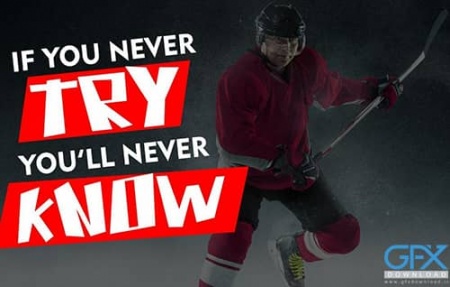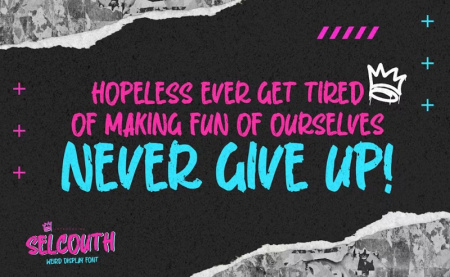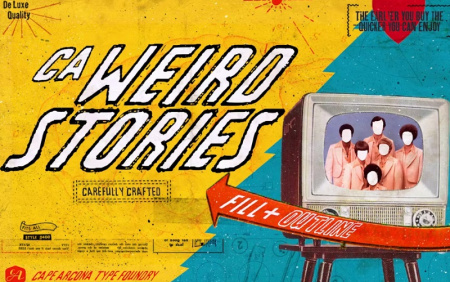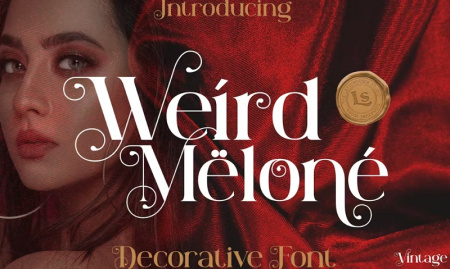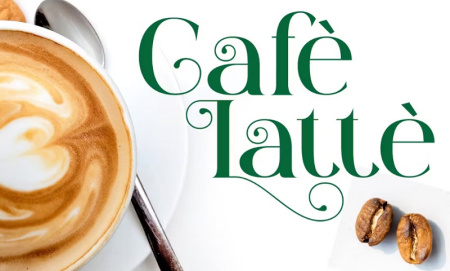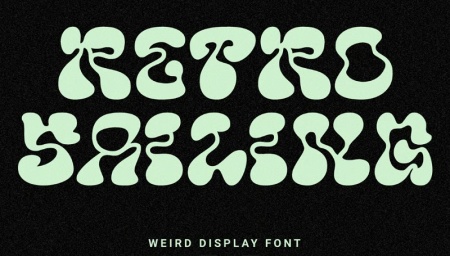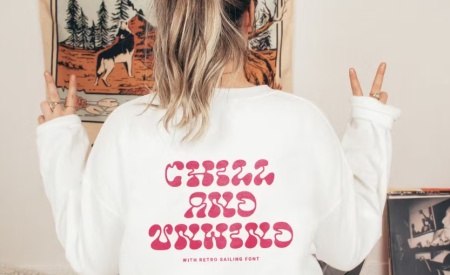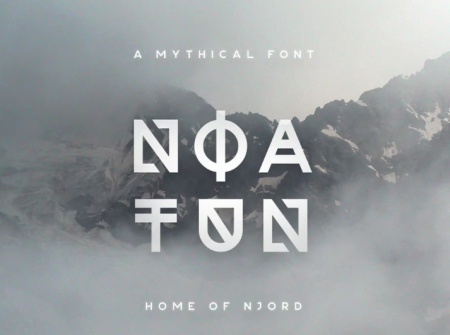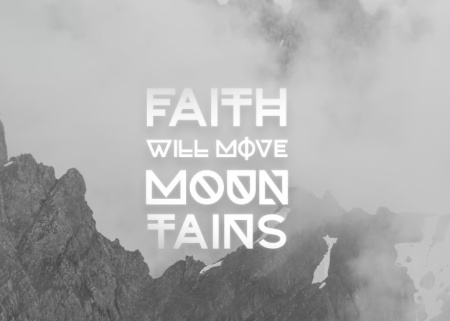
مجموعه فونت انگلیسی عجیب غریب از جی اف ایکس دانلود. این مجموعه شامل 5 فونت انگلیسی به سبک عجیب و غریب است که مناسب برای طراحی های گرافیکی، تبلیغاتی، برچسب، بسته بندی محصول، رویدادهای خاص، لوگو و ... می باشد. برای مشاهده پیش نمایش این مجموعه فونت عجیب و غریب انگلیسی در ادامه با ما همراه باشید.
فونت های عجیب و غریب انگلیسی
Retro Sailing نام فونت عجیب و غریب انگلیسی می باشد که برای طراحی کالا، پوستر، جلد و پست های رسانه های اجتماعی مناسب است. شامل حروف بزرگ، کوچک، اعداد، نقطه گذاری و چند زبانه. با فرمت های Otf، Ttf و Woff ارائه شده است.
فونت عجیب غریب و جذاب انگلیسی
این فونت عجیب غریب و جذاب انگلیسی با نام Noatun Typeface از سایت جی اف ایکس دانلود در اختیار شما قرار داده شده است. این فونت به سبک هندسی مناسب برای عناوین، لوگو ها و نقل قول های کوتاه و ... می باشد. این فونت شامل پشتیبانی چند زبانه، حروف بزرگ، اعداد و علائم نگارشی است.